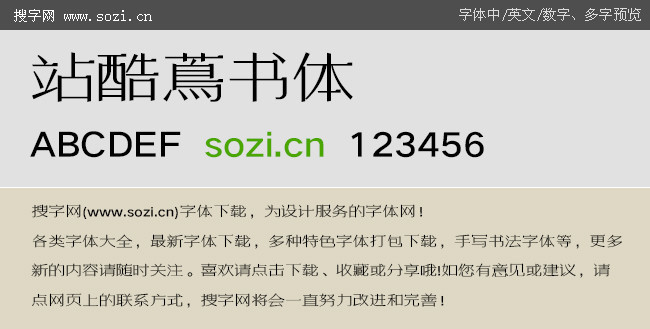
站酷蔦書(shū)體
搜字網(wǎng)給大家提供一款站酷蔦書(shū)體中文字體下載,創(chuàng)作靈感源于日本蔦屋書(shū)店,融合了蔦屋書(shū)店和蔦屋家電的筆畫(huà)特點(diǎn),筆畫(huà)橫細(xì)豎粗,整體字形扁正俊秀,適用于標(biāo)題字。全字庫(kù)簡(jiǎn)繁體共計(jì)9913個(gè)字符。(本字體為個(gè)人非商用版,如需要商用請(qǐng)聯(lián)系作者購(gòu)買(mǎi)版權(quán))